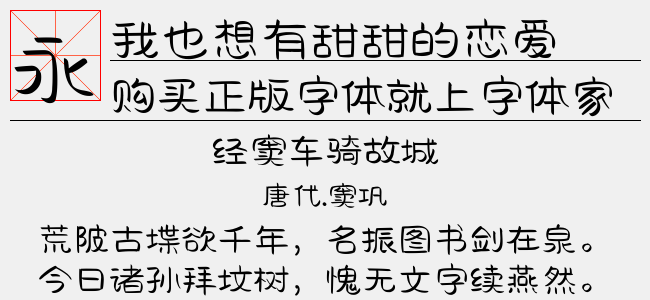
我也想有甜甜的恋爱
字体作者:文道字库
字体名称:我也想有甜甜的恋爱
字体家族:文道字库
字体公司:文道字库
我也想有甜甜的恋爱
我也想有甜甜的恋爱是文道字库推出的一款非常不错的艺术字体,风格比一般的字体更有特色,连贯字迹显得干练而不凌乱,清新简明,具有很好的视觉感,适合应用于艺术设计、平面宣传设计、网页设计,书法字帖等领域,欢迎喜欢我也想有甜甜的恋爱字体的朋友前来下载使用。